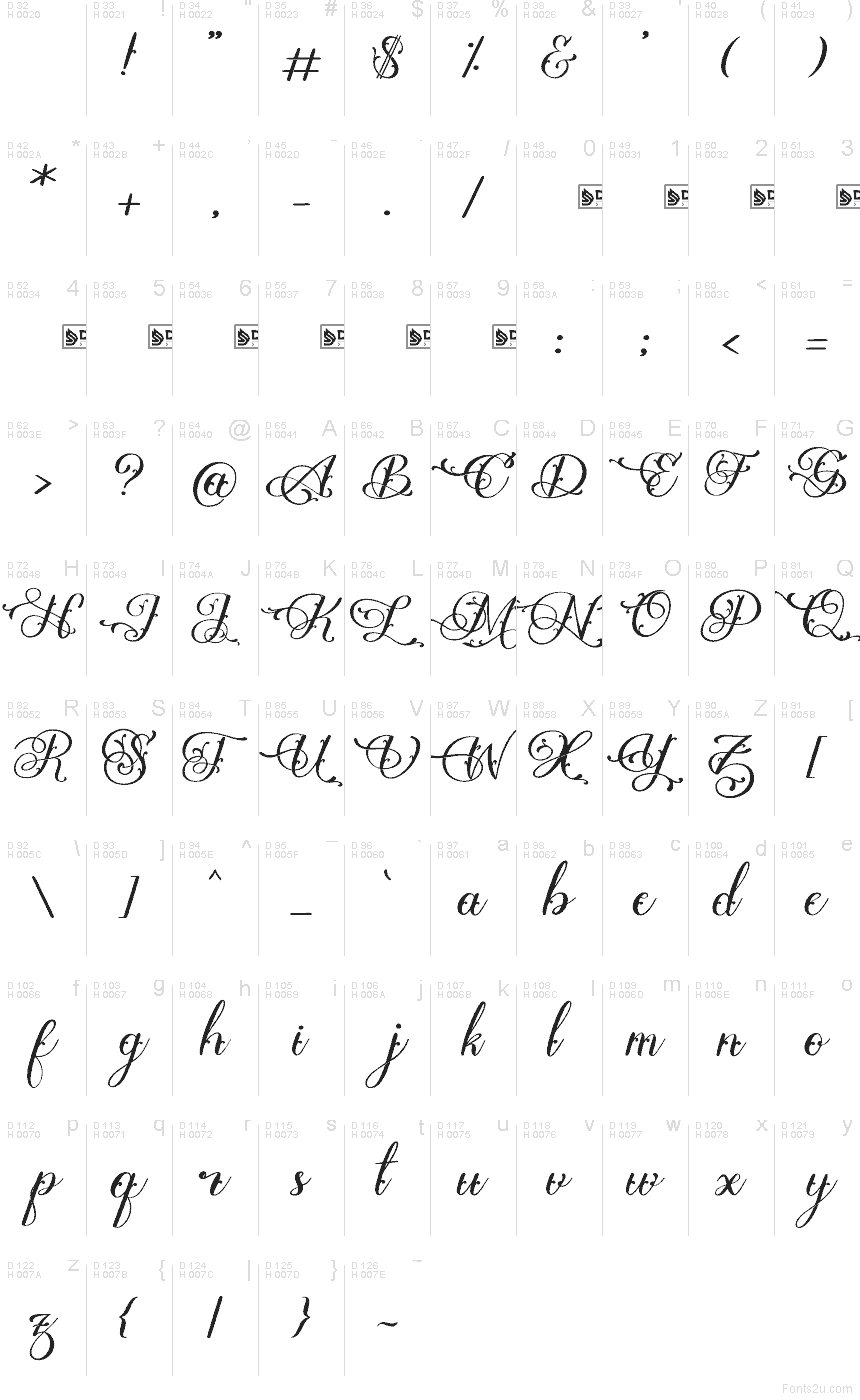
Singaley, una tipografía caligráfica gratuita de Denustudios, apuesta por un estilo romántico y de alto contraste con florituras envolventes y trazos largos y sinuosos. Las letras se perciben ligeras y teatrales, con uniones finas, puntos redondeados y curvas generosas que permiten que los ornamentados caracteres iniciales y las descendentes pronunciadas cobren todo el protagonismo.
Es ideal para papelería de bodas, packaging de belleza, identidad de marca para cafeterías, portadas y tarjetas de títulos donde el dinamismo es clave. Esta fuente gratuita también funciona muy bien en logotipos o monogramas que buscan una seña de identidad memorable. Úsala cuando quieras que la letra marque el tono por sí sola, ya que esos trazos extendidos crean un ritmo decorativo incluso en palabras cortas.